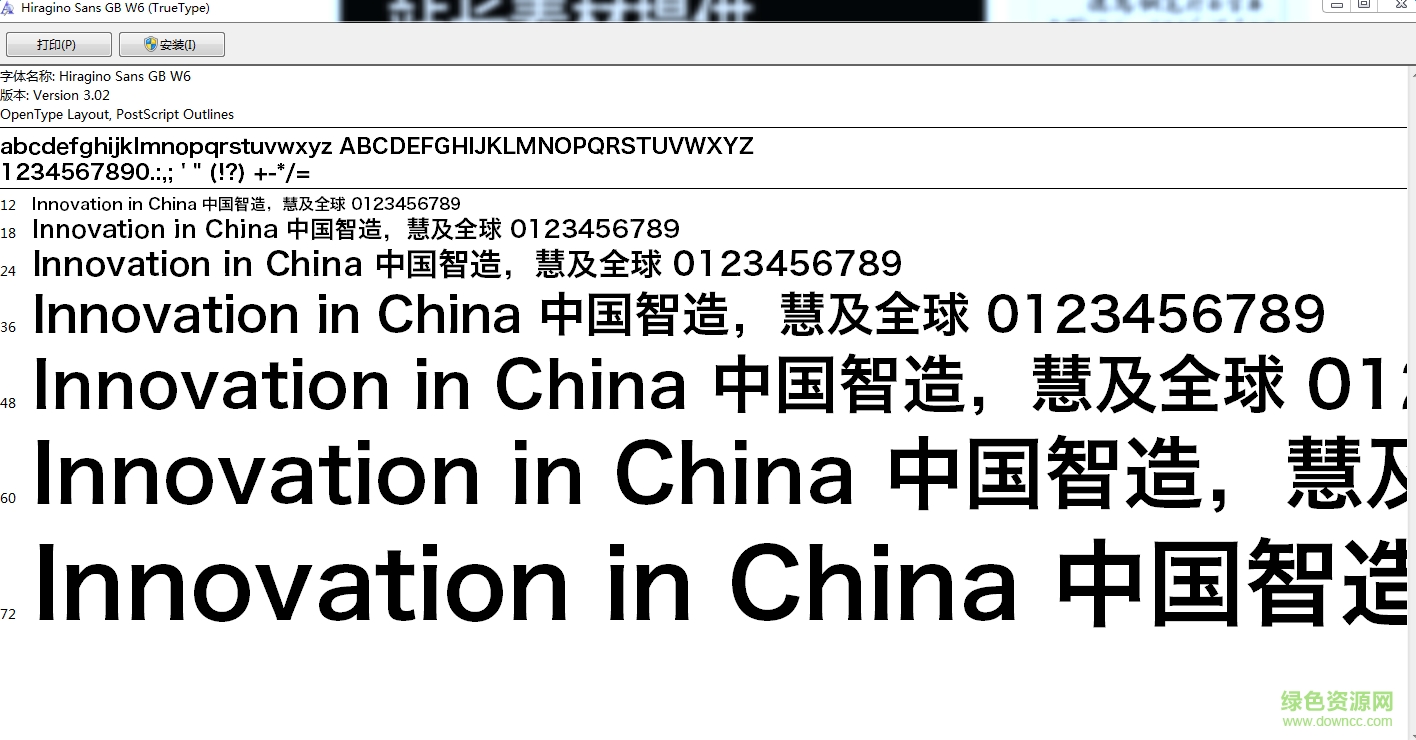
hiraginosansgb w6字體是一款半粗體字體,該字體也叫蘋果麗黑w6字體,字形端莊清晰,筆畫全部一樣粗細,非常易于閱讀,歡迎大家在綠色資源網(wǎng)下載!
hiraginosansgbw6字體非常適合美化設計使用,字形整體與現(xiàn)有的漢儀黑體系列并無太大出入,但在結構上更飽滿,細節(jié)更好。該字體用來做設計是很合適的